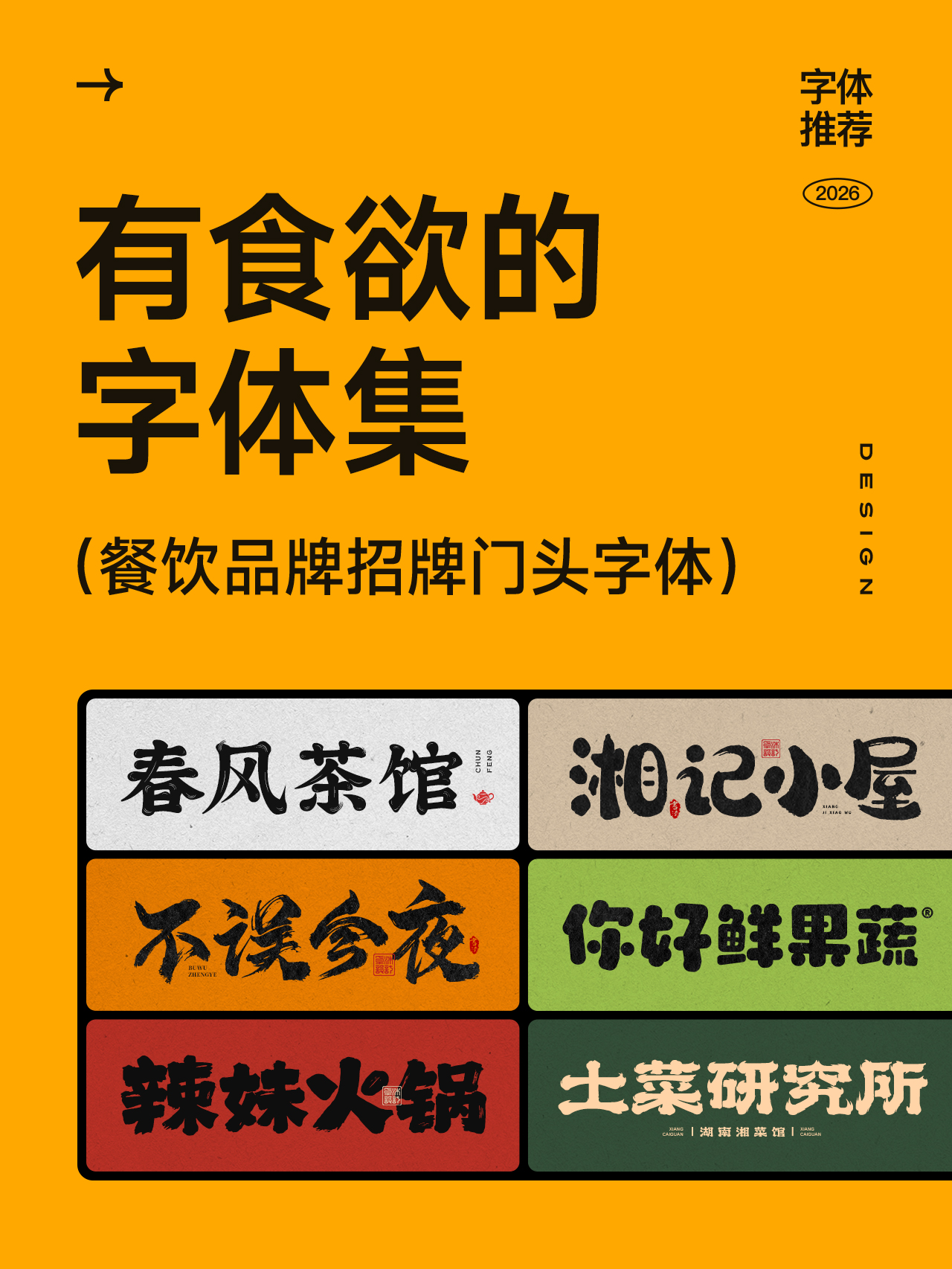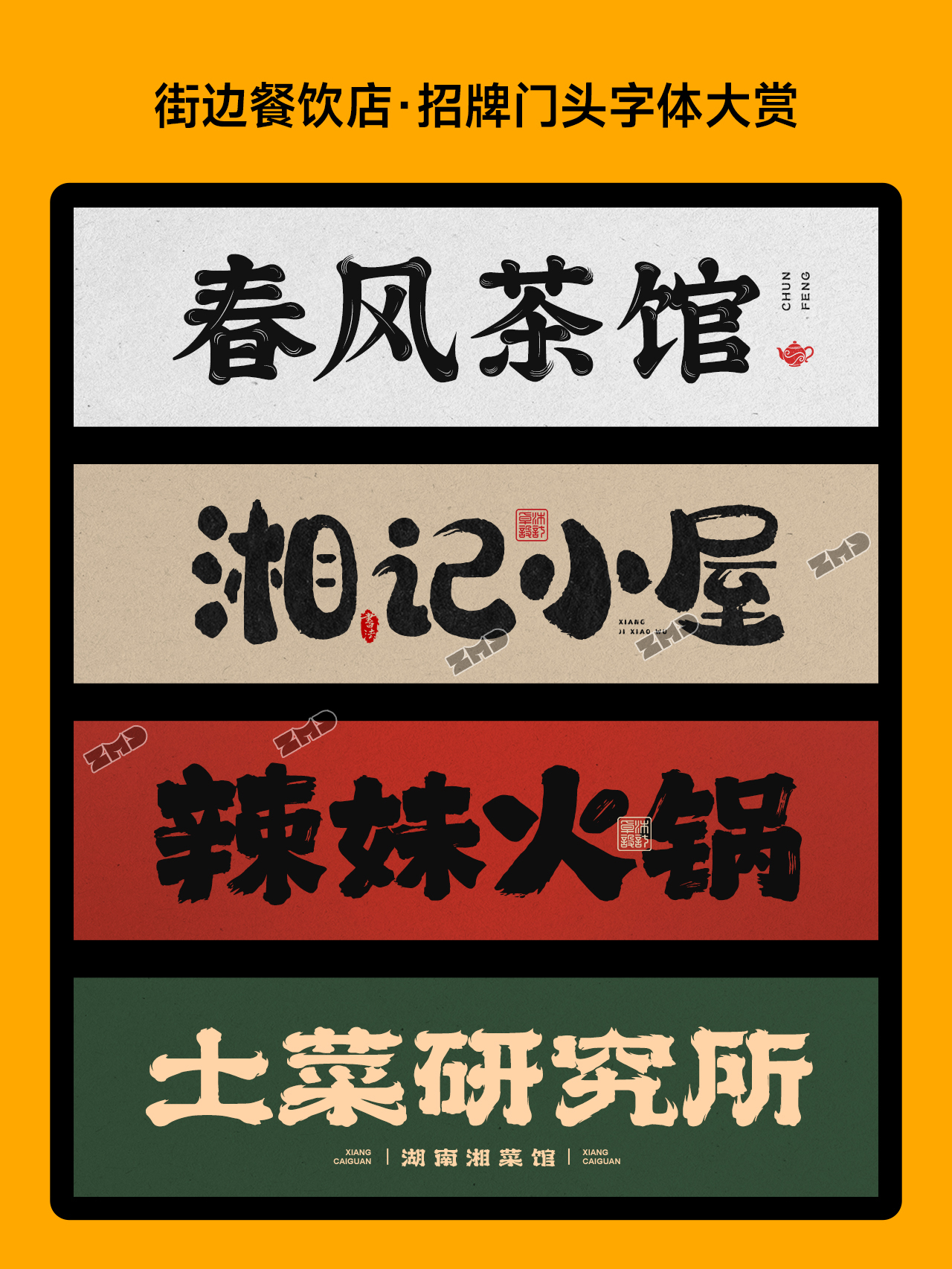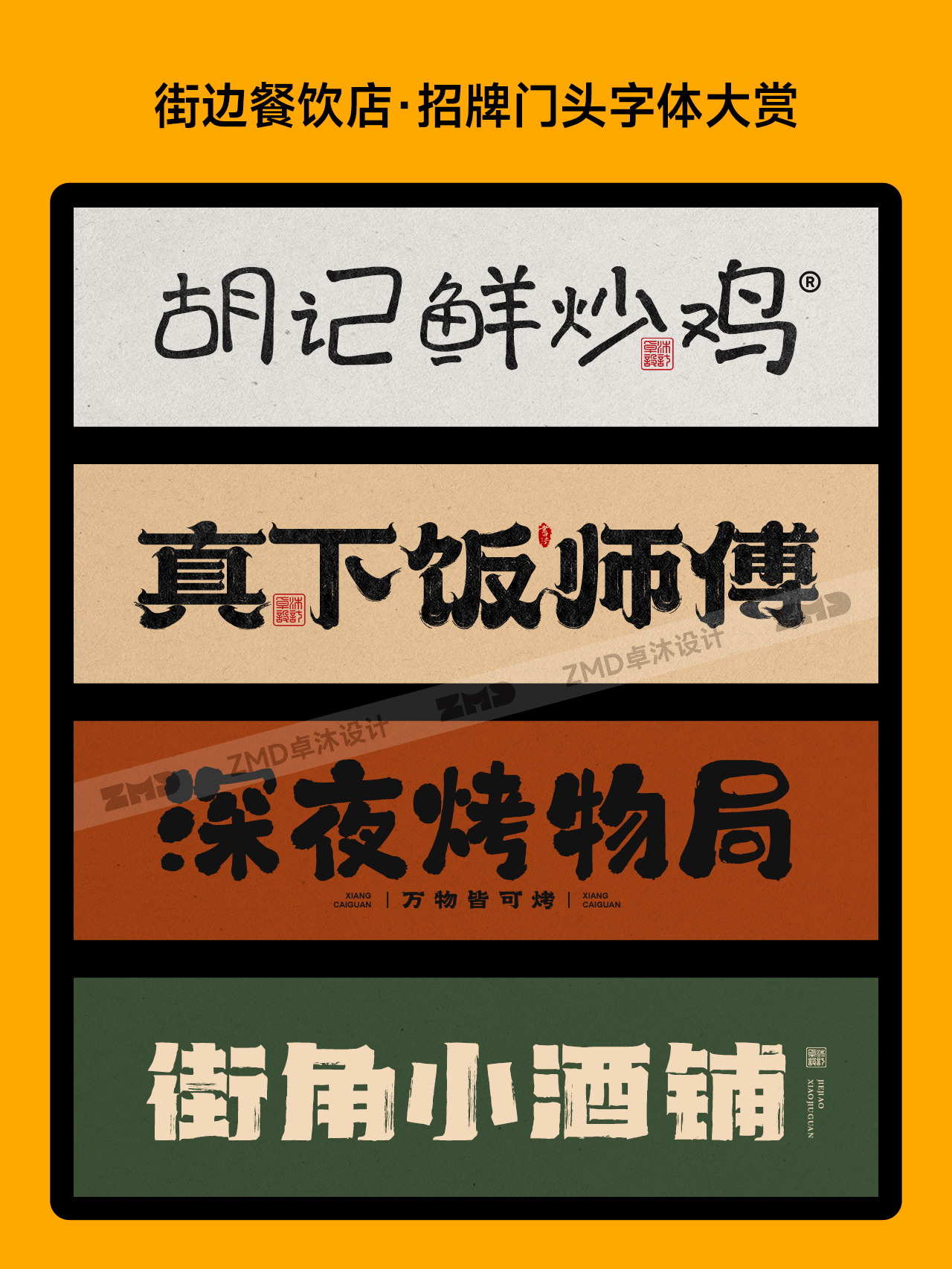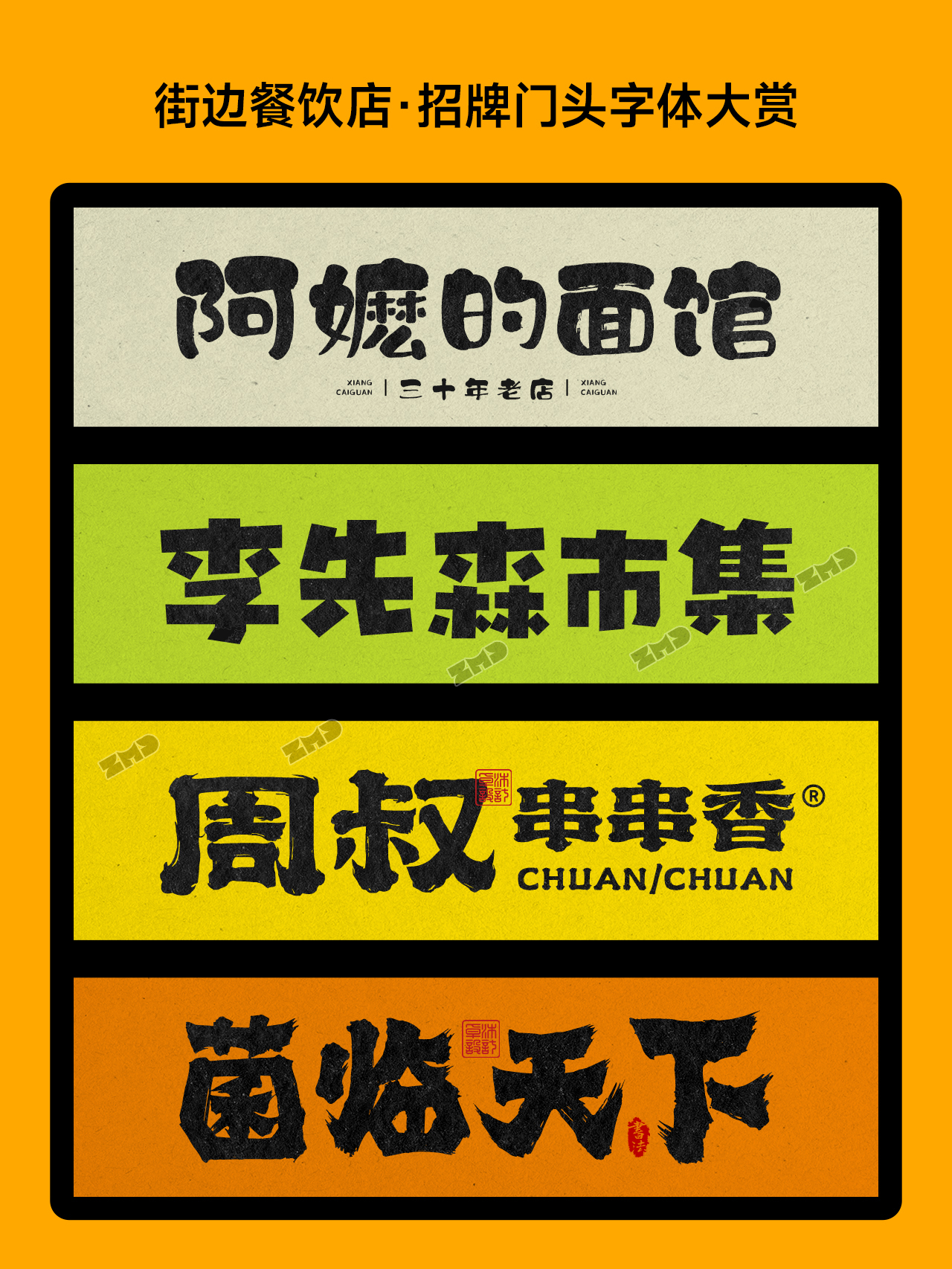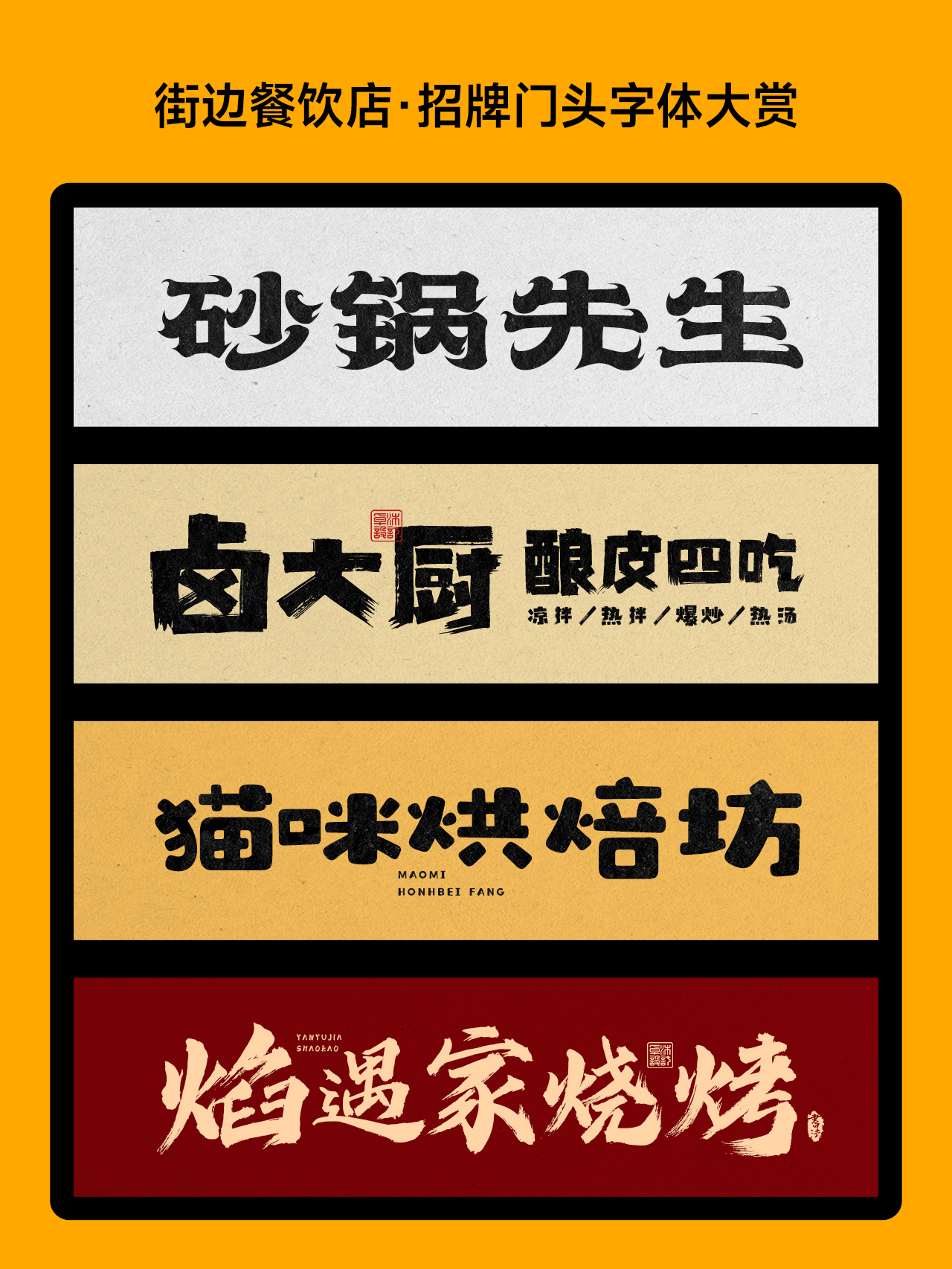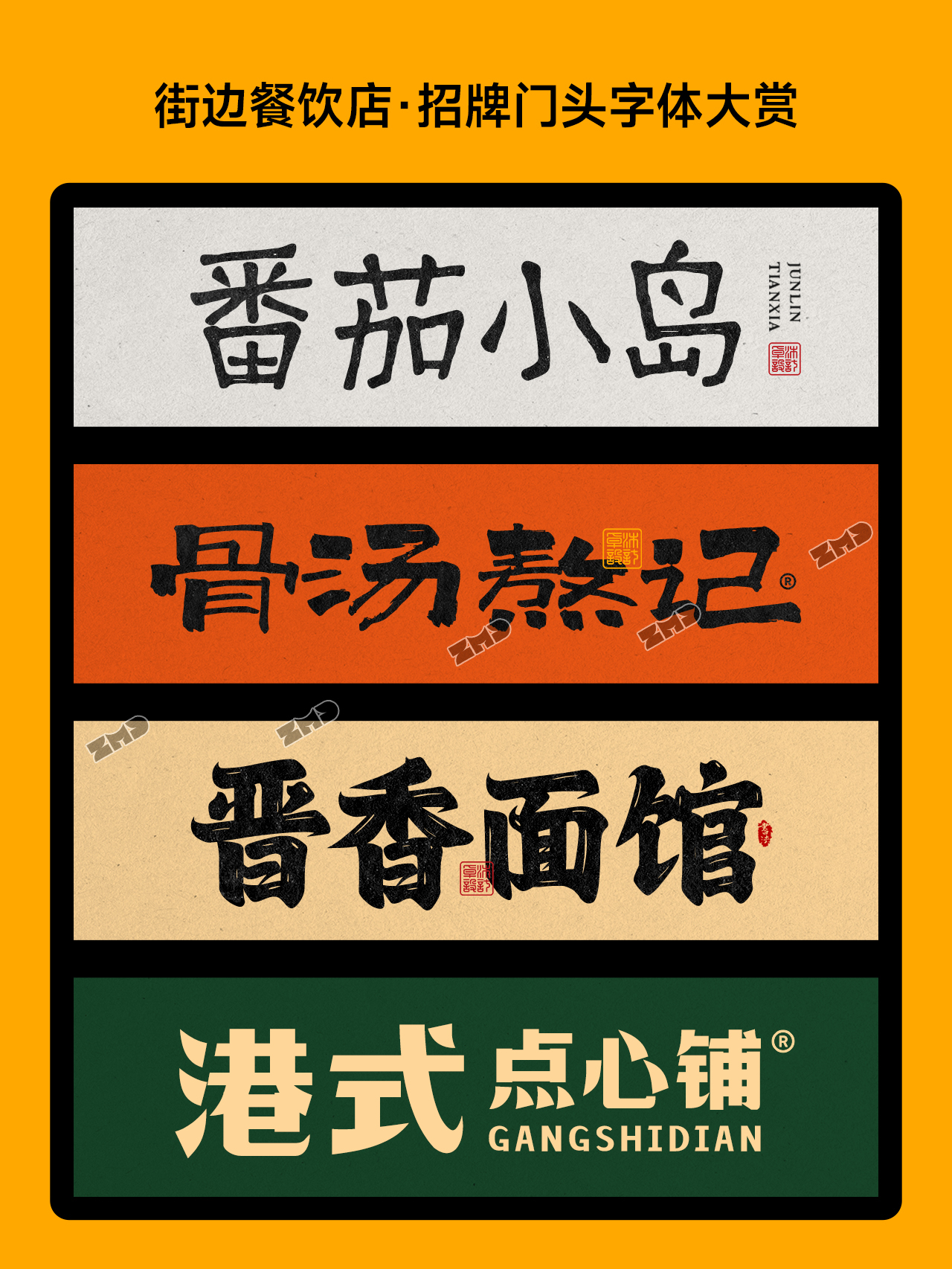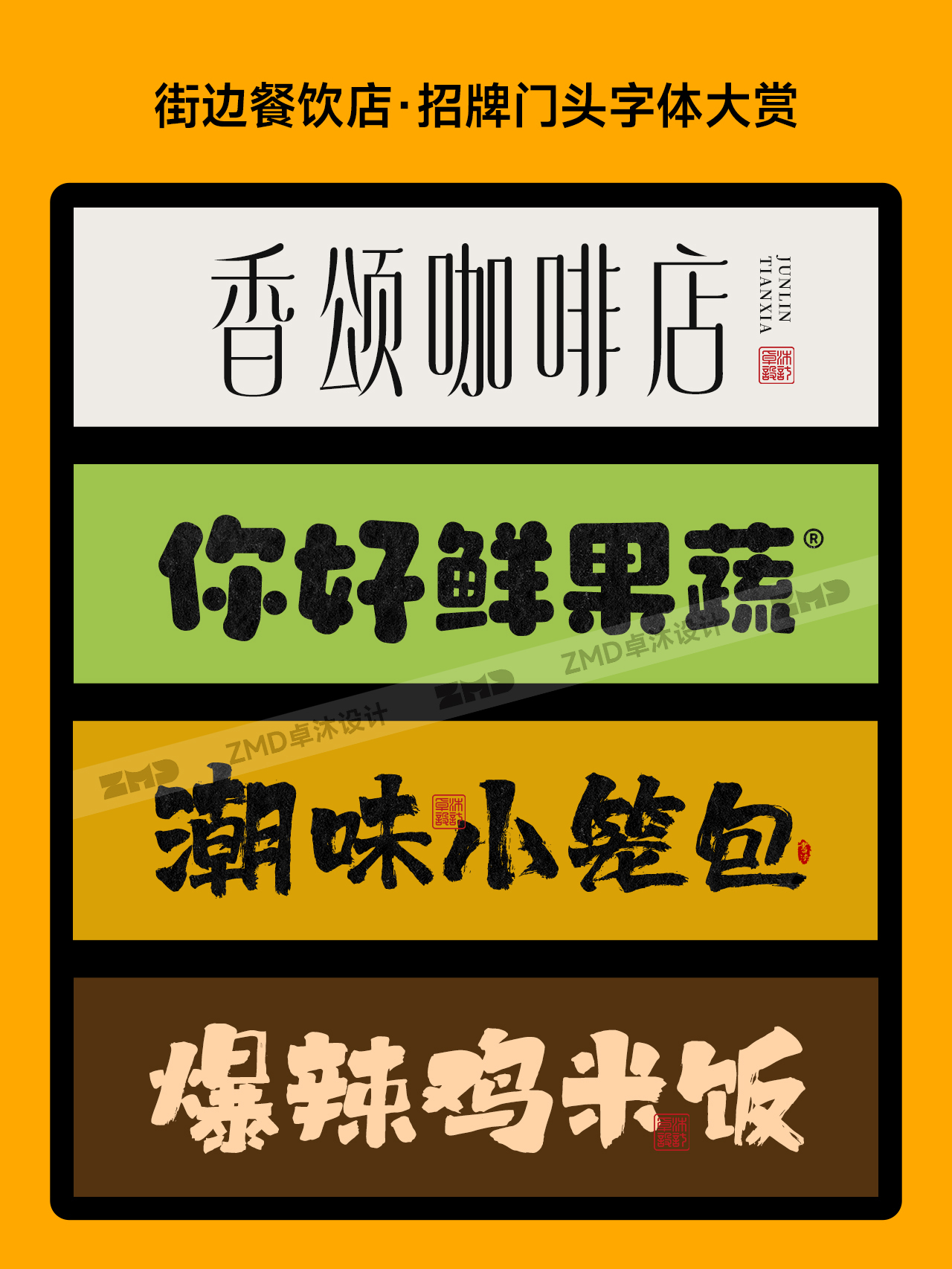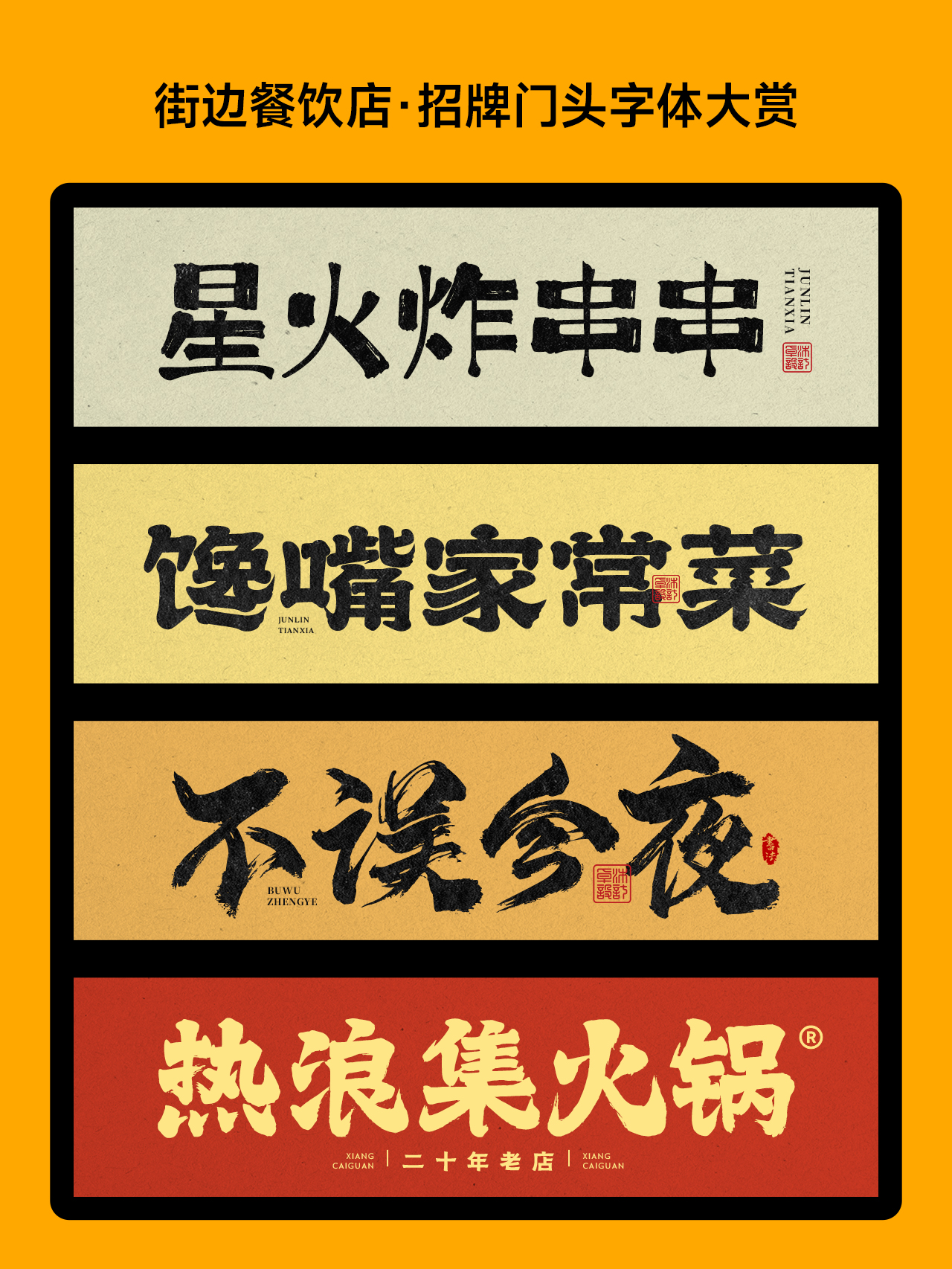
超有食欲!这些字体能把你看饿!餐饮品牌招牌门头标志logo设计字体欣赏!
一篇告诉你,街边餐饮店的招牌门头,到底该用什么样的字体才能吸客?
我帮你精挑细选了28款字体,卡通可爱风、手写国潮风都有~
可能看着会有点俗,但就是能一秒抓住路人眼球!
你喜欢这种风格的字体吗?
这次整理的字体,风格比较多,总有一个你能相中!